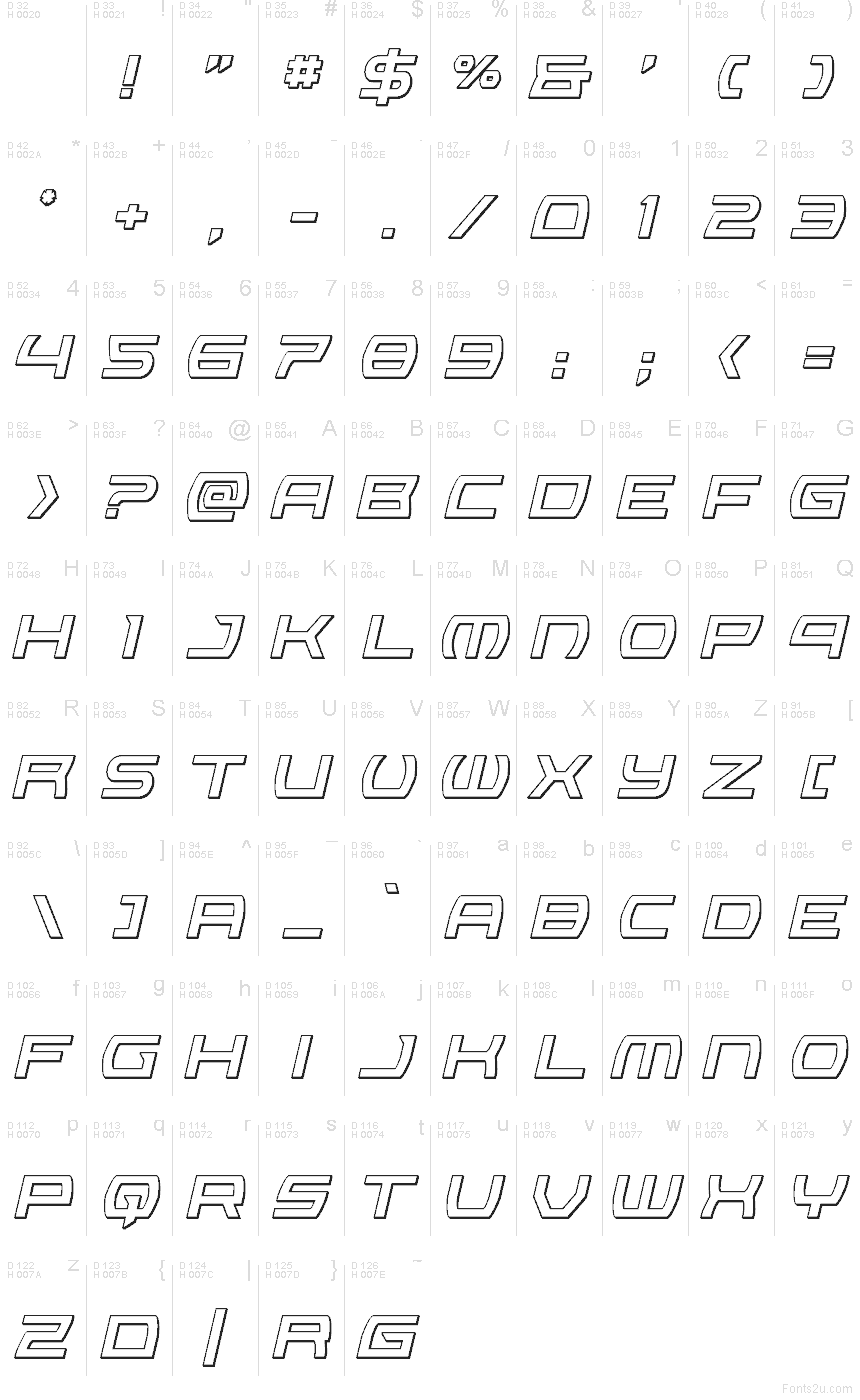
Icemaster 3D Italic
Icemaster 3D Italic von Iconian Fonts ist eine kostenlose, futuristische 3D-Display-Schriftart, die mit dem klaren, maschinell wirkenden Look von Arcade-Logos und Sci-Fi-Titeln überzeugt. Die Großbuchstaben lehnen sich in breiten, abgerundeten Blöcken nach vorne, während der konturierte 3D-Effekt für einen hohlen, extrudierten Look sorgt – kühl, metallisch und dynamisch, ohne überladen zu wirken.
Die Schrift passt perfekt zu Plakatüberschriften, Gaming-Branding, Albumcovern, E-Sport-Grafiken und Titelkarten, bei denen ein kostenloser Font Bewegung und eine markante, synthetische Oberfläche benötigt. Da die Buchstaben ihren dimensionalen Effekt bereits in sich tragen, eignet sich die Schrift hervorragend für kurze Schriftzüge, Monogramme und Titel, die eine starke Silhouette bei wenig Text erfordern.